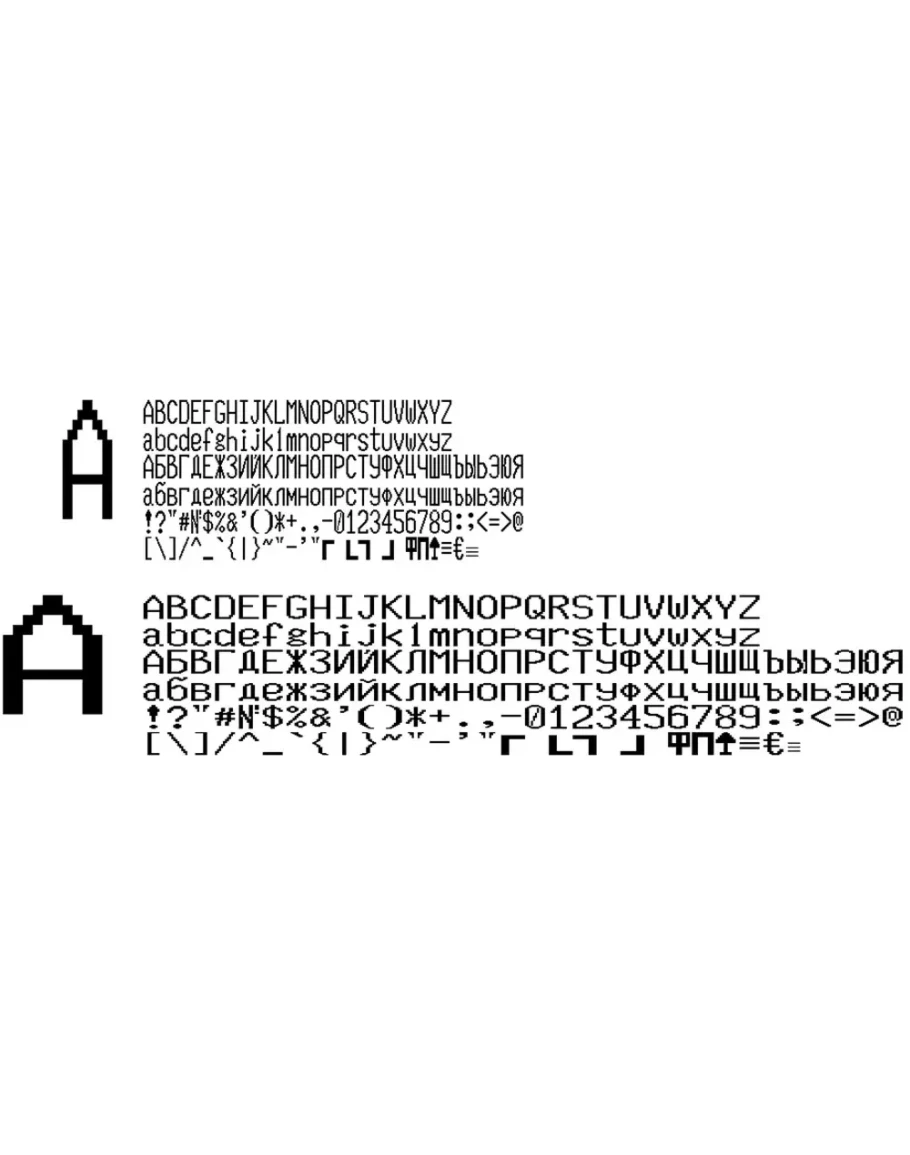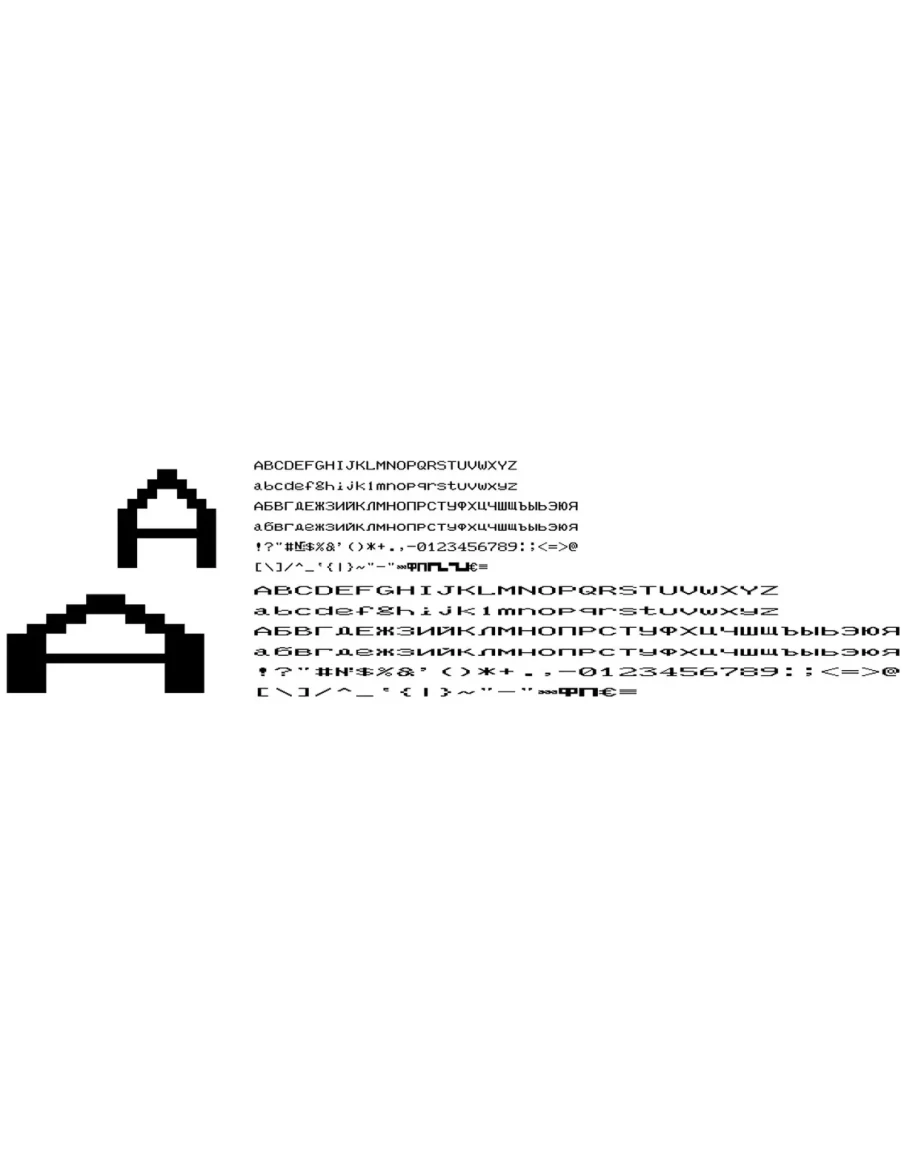
Данный набор шрифтов "Розничные сети 2" кассового аппарата ФЕЛИКС-РК содержит 2 версии шрифтов (4 и 5) в формате TTF (русские и английские буквы) для использования в программе Microsoft Word. В архиве находятся стандартные и широкие шрифты для каждой версии (всего 4 шрифта) в формате TTF и шаблон варианта чека, который, в частности, используется во многих сетях магазинов розничной торговли, например "Рубль Бум". Вам остается только установить шрифты в систему (обычно C:\WINDOWS\Fonts), открыть шаблон и начать редактирование. Печатать чеки предпочтительно на термопринтере, на кассовой термоленте. Хотя можно печатать и на струйнике и лазерном, с возможностью вывода на факсовую бумагу. Лучшее качество, естественно, при печати на термопринтерах.
Набор 4 шрифтов ККМ "Розничные сети 2" Феликс-РК 4 и 5